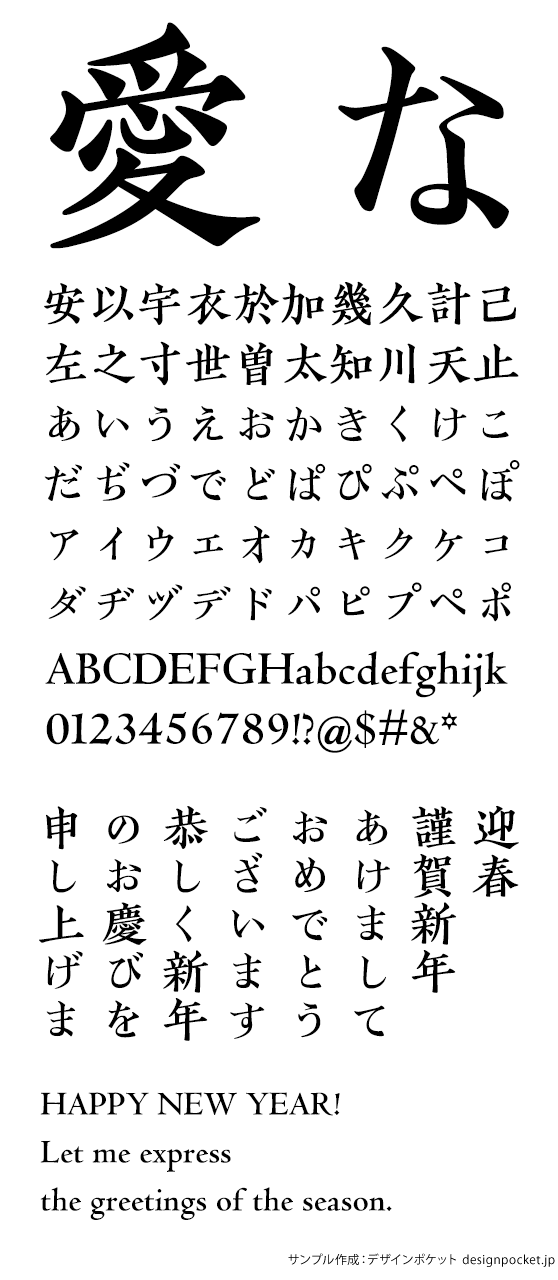
宋朝体
有限会社今田欣一デザイン室
KOこみなみ陳起B
KOKoMinamiChinki-B
『本邦活版開拓者の苦心』(津田三省堂、1934)の序文から復刻した「みなみ」の字面を小さくした「こみなみ」に、『南宋羣賢小集』(陳宅書籍鋪、1208—1264)にもちいられた字様をもとに翻刻した臨安宋朝体「陳起」、ニコラ・ジェンソンの活字を使用したプリニウス著『博物誌』(1472)から復刻したヴェネチアン・ローマン体「K.E.Aries」を組み合わせた「KOこみなみ陳起M」のファミリーで、ボールド・ウエイトです。